日本語の美しさを、たった一文字で。
ひらがなの最初の文字「あ」。 シンプルでありながら、曲線と直線が調和したこの文字には、日本語タイポグラフィの魅力が凝縮されています。
このページでは、さまざまなフォントで表現された「あ」の表情をお楽しみいただけます。 明朝体の優雅さ、ゴシック体の力強さ、手書き風の温かみ、デザイン書体の個性—— 同じ「あ」でも、フォントが変わればこんなにも印象が変わります。
お気に入りの「あ」を見つけてください。 フォント選びの参考に、デザインのインスピレーションに、 あるいは純粋に文字の美しさを味わうひとときに。
ゆっくりとスクロールして、「あ」の世界をお楽しみください。
あ:フォント:筑紫アンティークL明朝
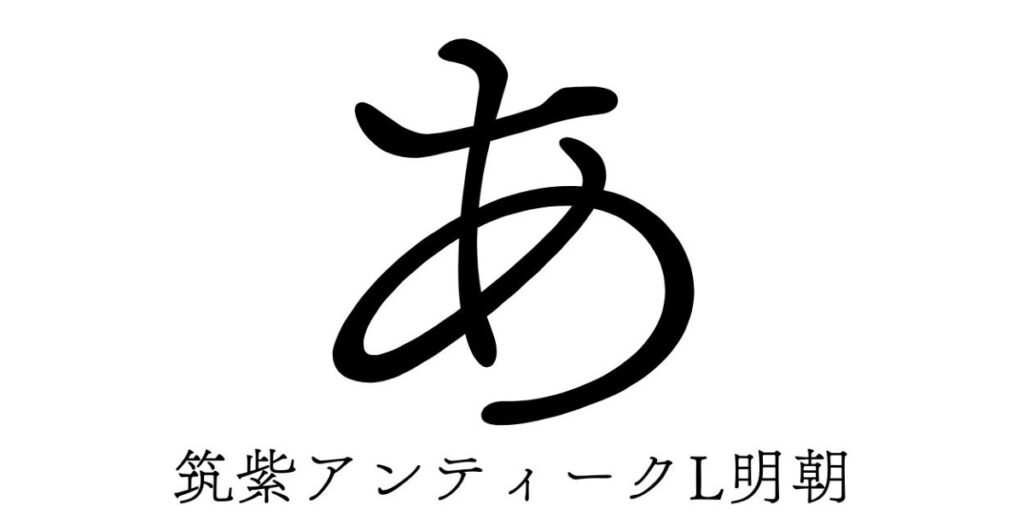
あ:フォント:Sモトヤ大楷
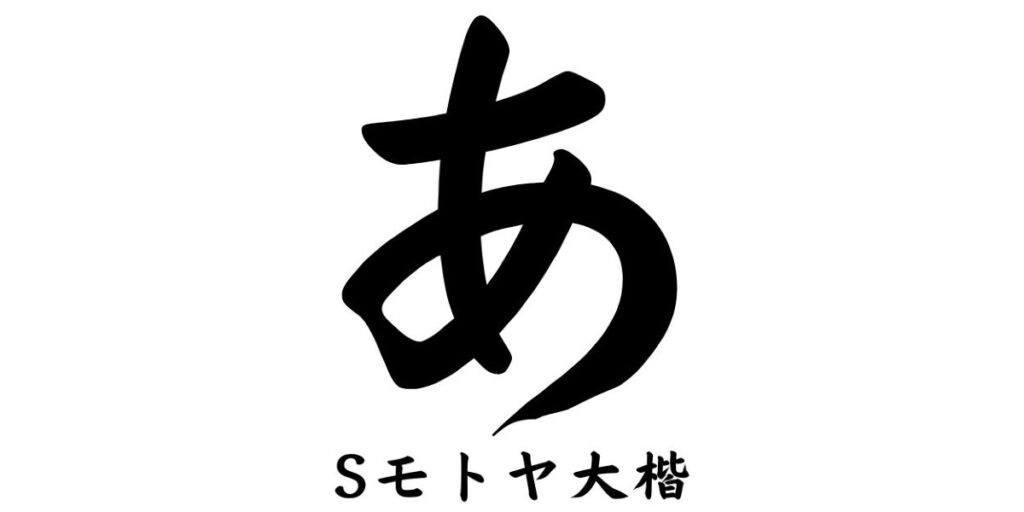
あ:フォント:セイビオオキド
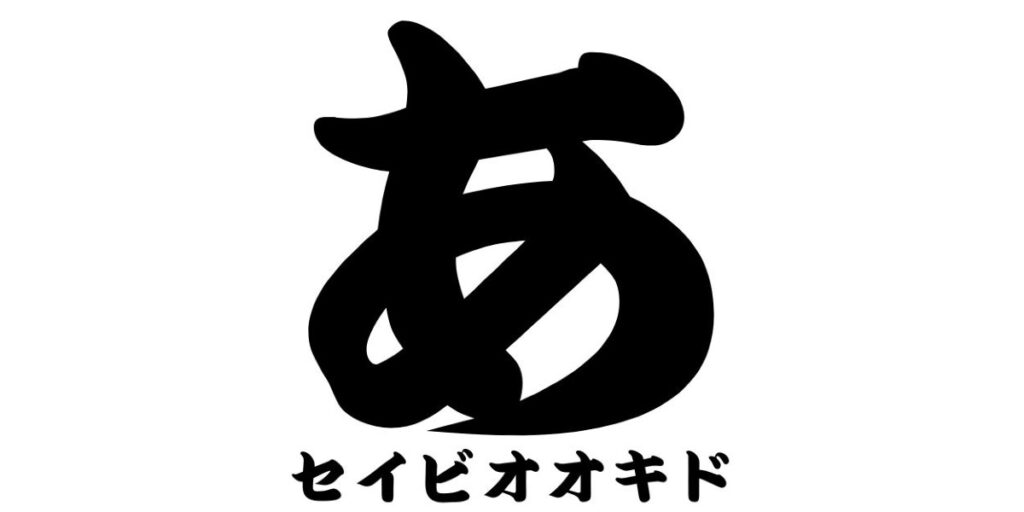
あ:フォント:モトヤ明朝みやび
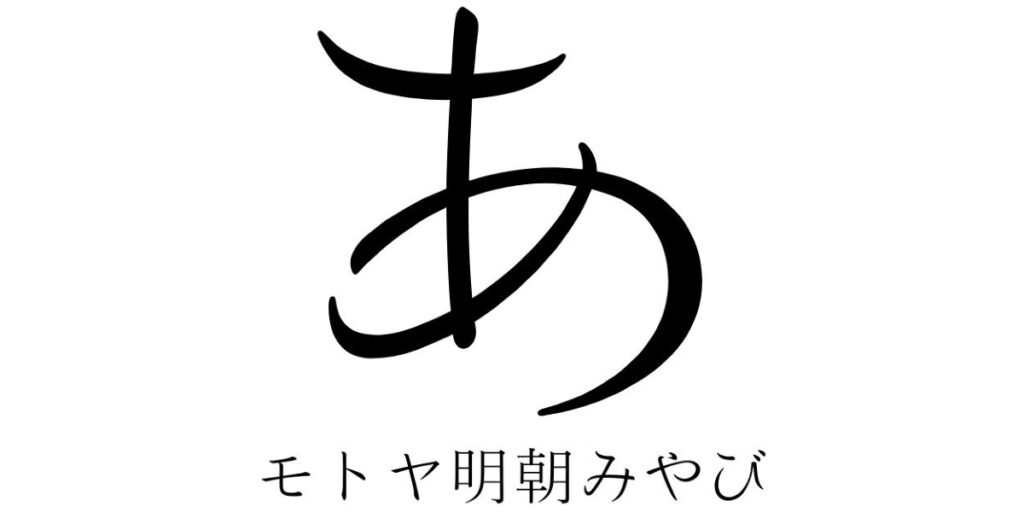
あ:フォント:HGゴシック
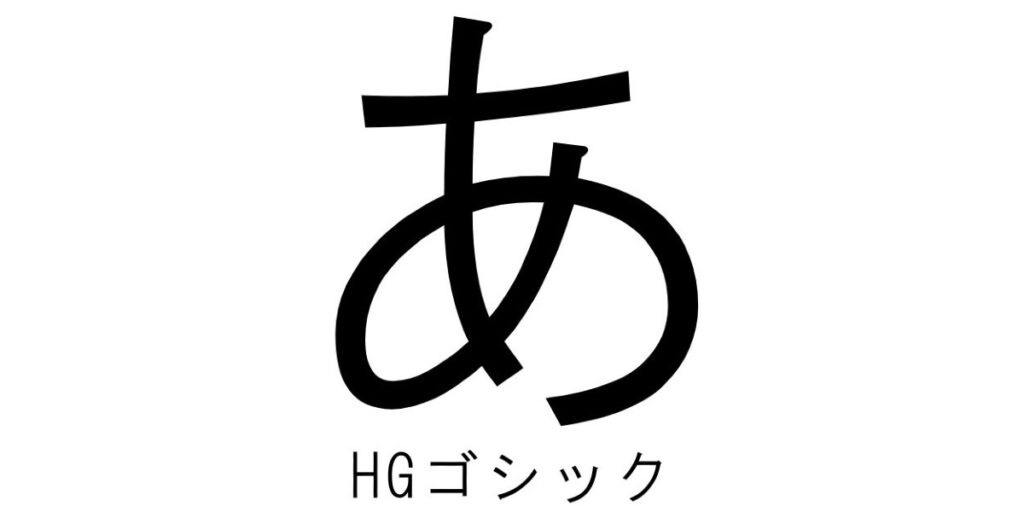
あ:フォント:遊ゴシック体
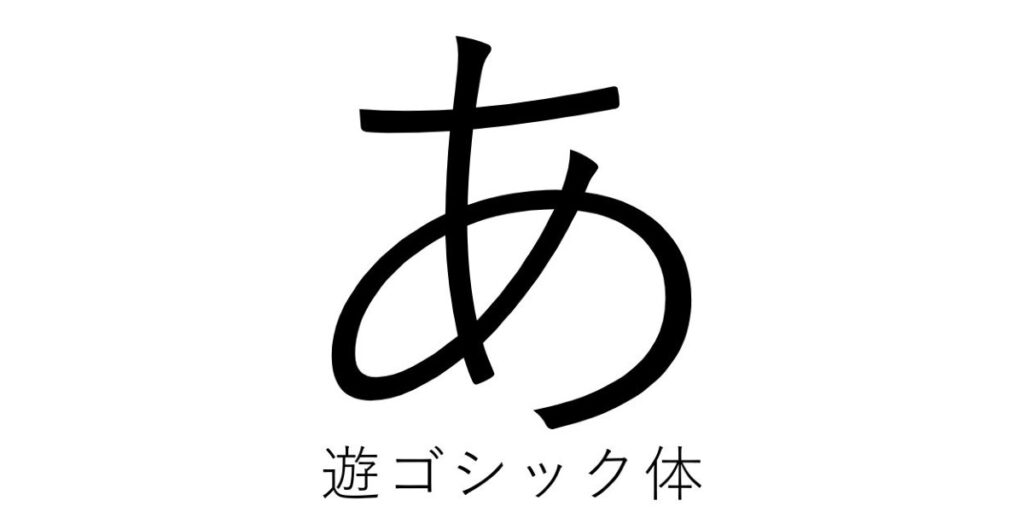
あ:フォント:鉄瓶ゴシック
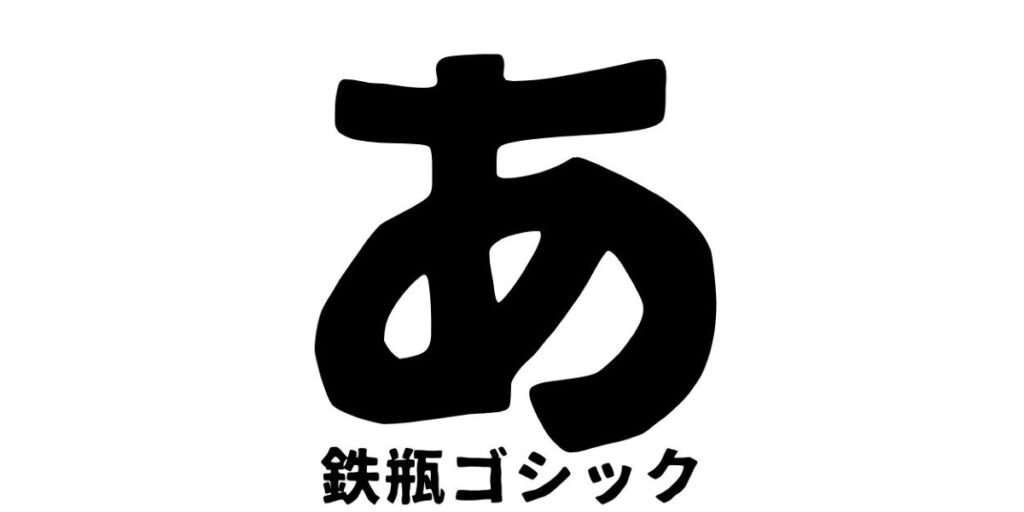
あ:フォント:せのびゴシック
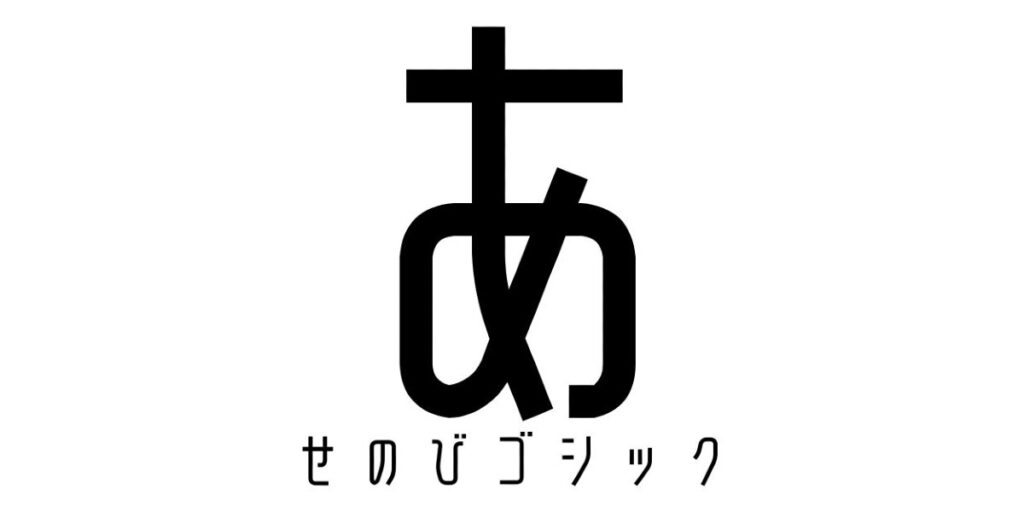
あ:フォント:JKゴシック
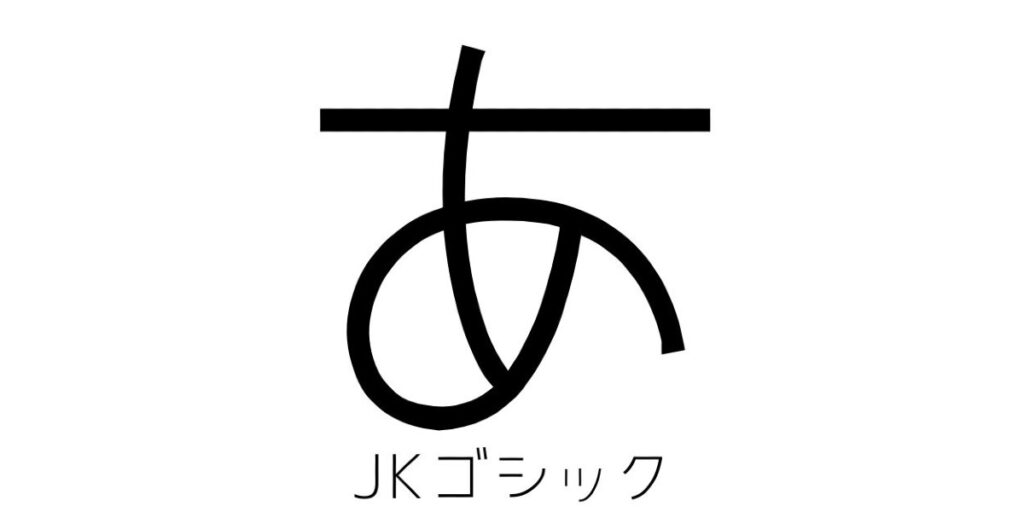
あ:フォント:モトヤステンシルアポロ
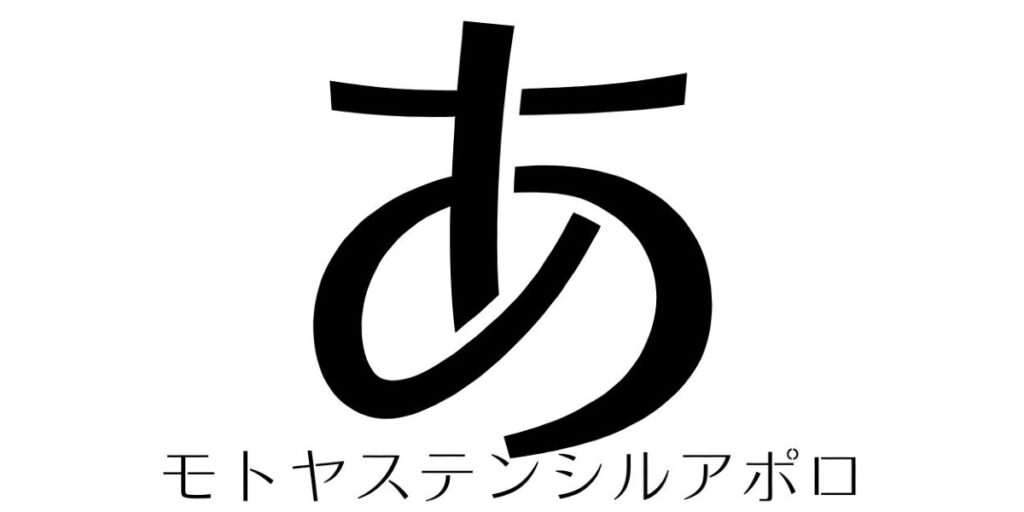
あ:フォント:UDモトヤ明朝
あ:フォント:モトヤ明朝モダン
あ:フォント:モトヤ明朝オールド
あ:フォント:あおぞら明朝
あ:フォント:XANA明朝フォント
あ:フォント:装甲明朝
あ:フォント:刻明朝
あ:フォント:梅明朝
あ:フォント:ドット明朝12
あ:フォント:ドット明朝16
あ:フォント:はんなり明朝
あ:フォント:Morisawa 勘亭流 StdN U
あ:フォント:HG江戸文字勘亭流
あ:フォント:モトヤ教科書
あ:フォント:UDデジタル教科書体NPL
あ:フォント:Sモトヤ新楷書
あ:フォント:イワタ隷書体
あ:フォント:HG創英イオリ書体
あ:フォント:御山毛筆
あ:フォント:花風ペン字体